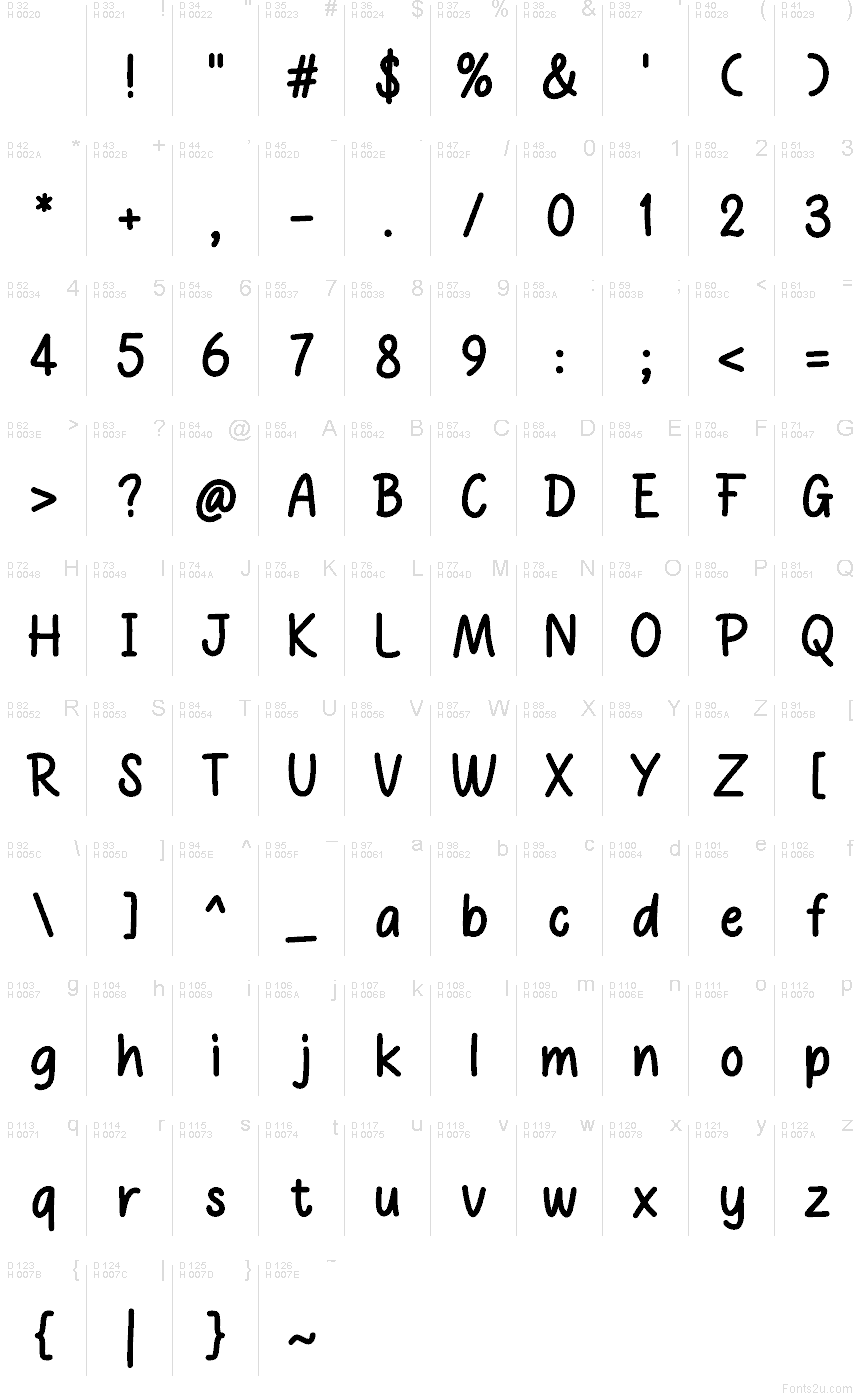
Monny Cartoon
La police Monny Cartoon du Hello Good Studio est une écriture manuscrite gratuite aux traits arrondis et irréguliers, au rythme léger et cartoon. Les lettres semblent dessinées naturellement, avec des courbes douces, des jointures compactes et un aspect manuscrit convivial qui garde le texte vivant sans jamais paraître brouillon.
Monny Cartoon est une police gratuite idéale pour le branding destiné aux enfants, les invitations, les menus de café, les titres d'affiches et les visuels réseaux sociaux, grâce à son style décontracté façon lettrage à la main. Elle convient également aux logos, emballages, cartes de vœux et textes courts où l'aspect « fait main » prime sur la formalité.